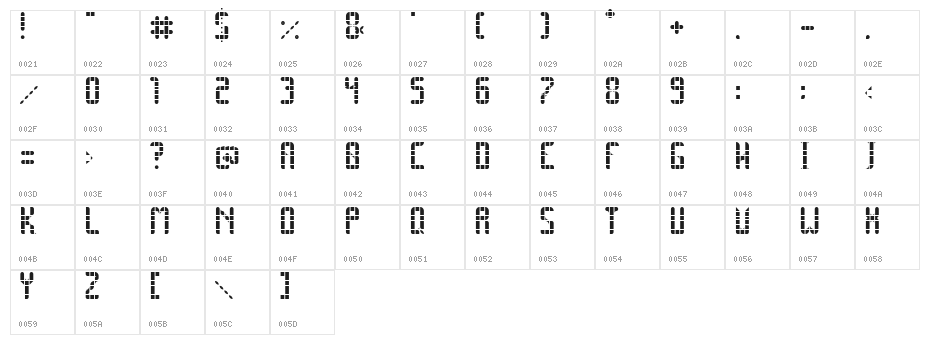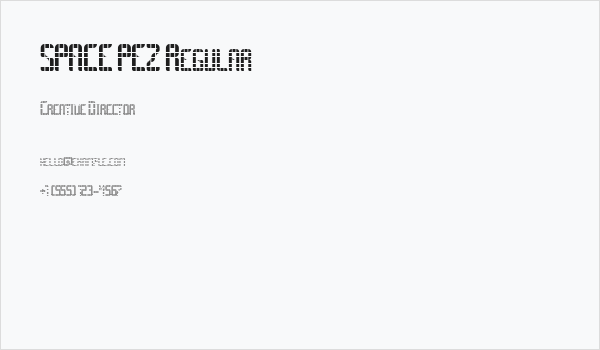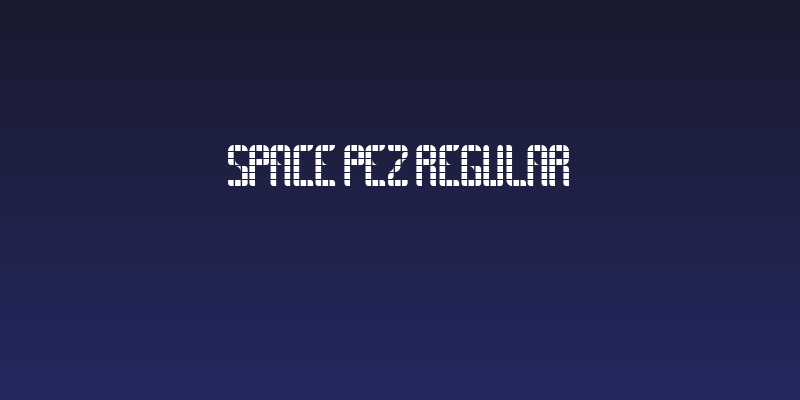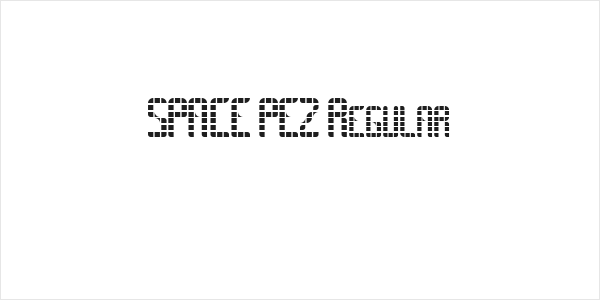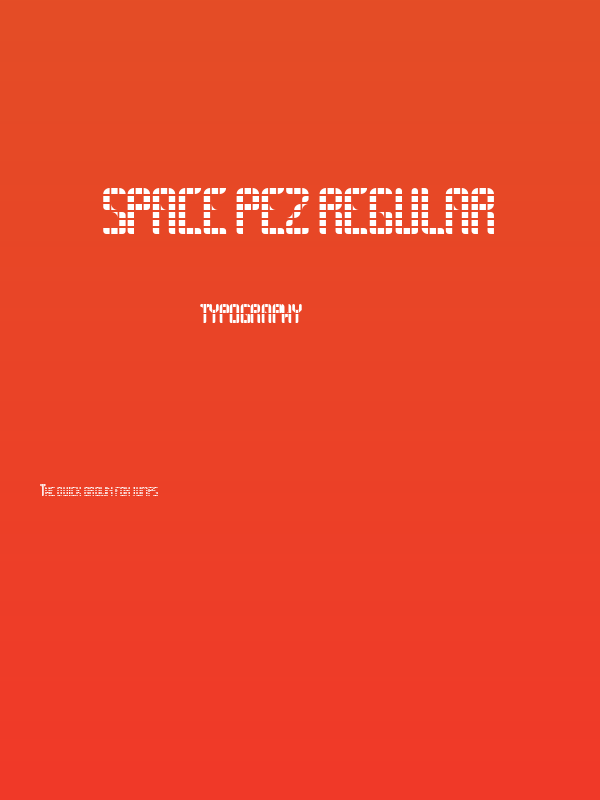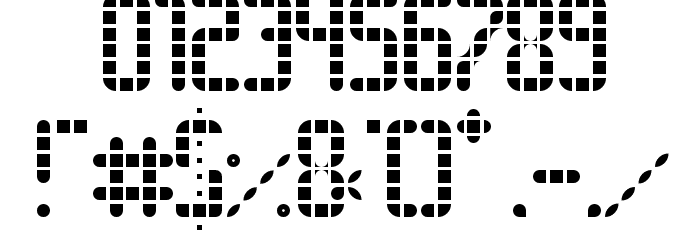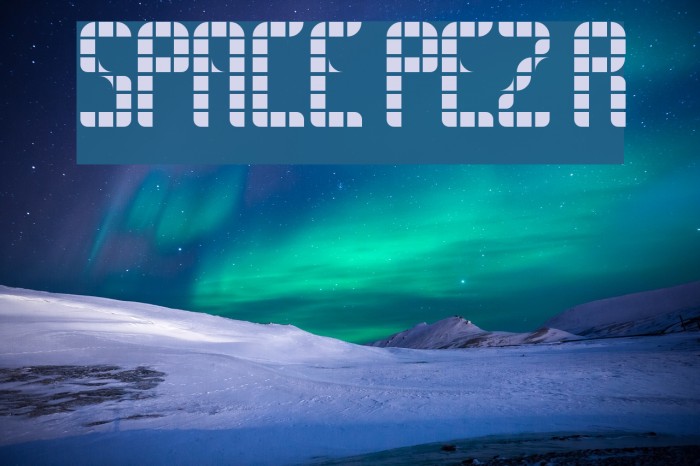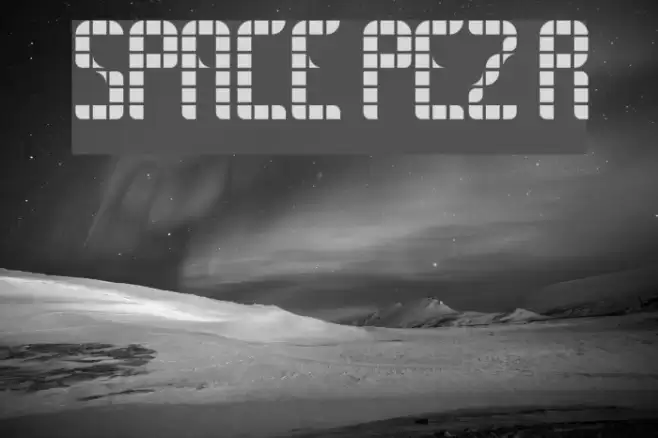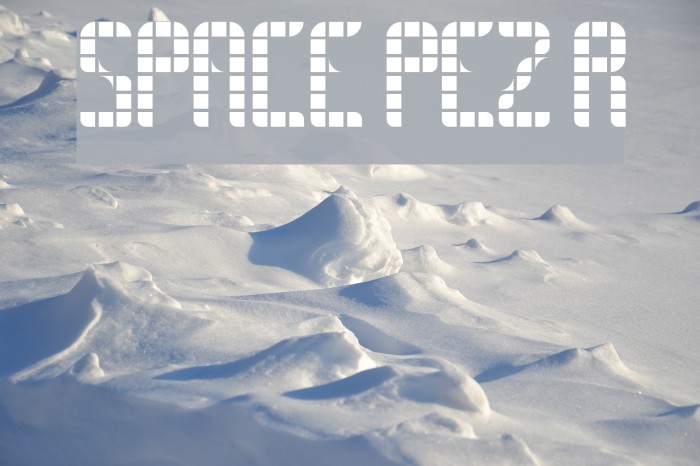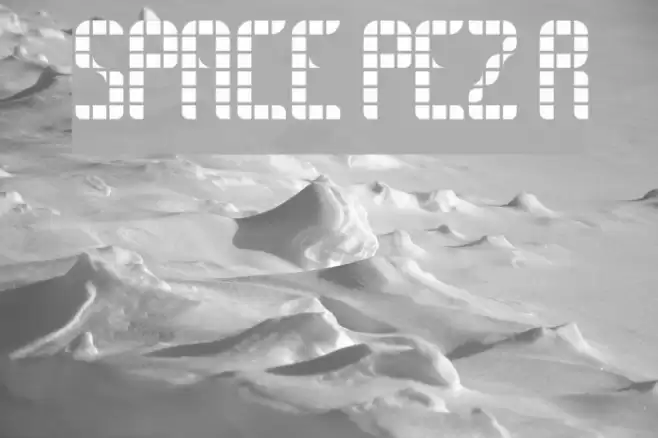
SPACE PEZ Regular Font
| Vorgeschlagene Projekte | Ideal for technology branding, digital art projects, video game interfaces, and sci-fi themed designs. |